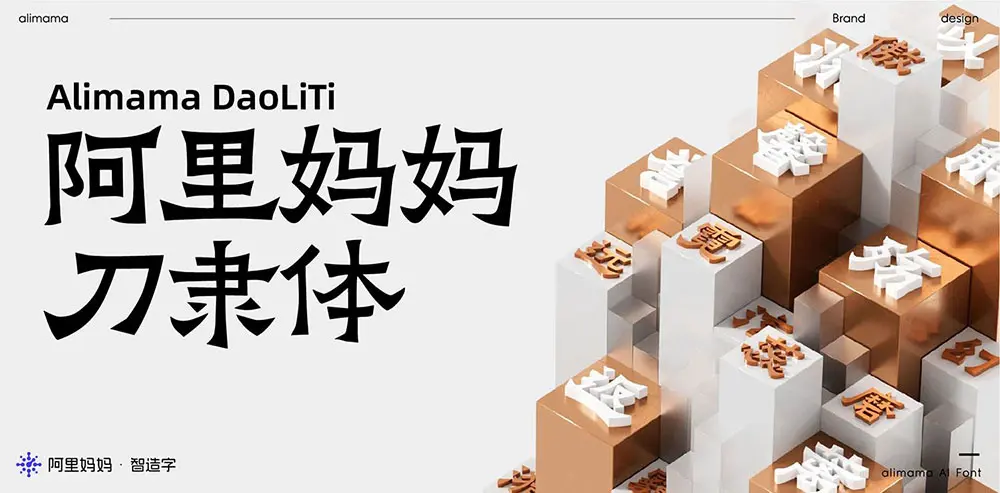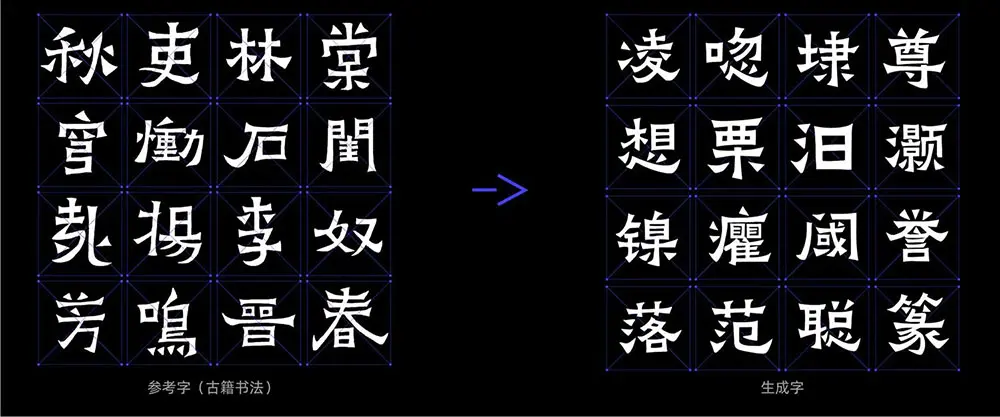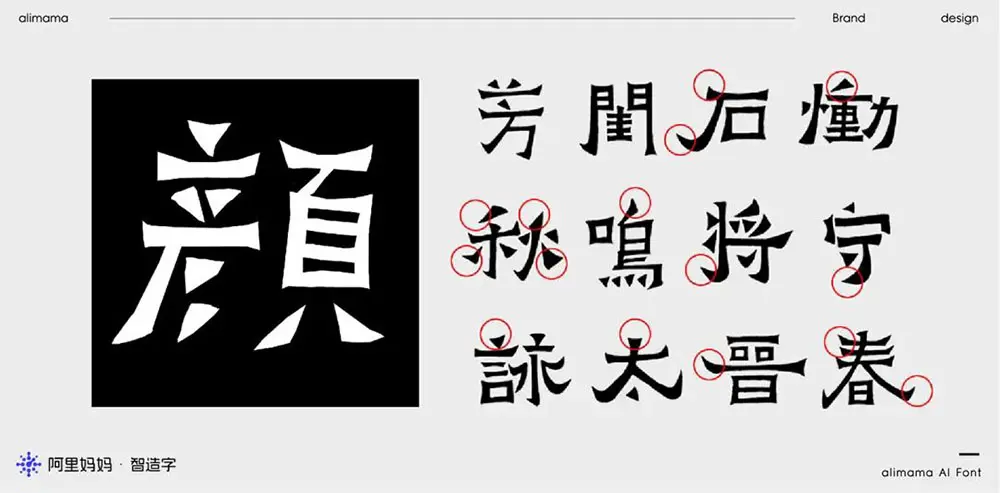
阿里媽媽刀隸體為中文簡體字庫,收納的中文字符包括但不限於GB2312,共計6763個漢字;英文大小寫共52個;常用標點符號共227個,總計7042個字符
設計說明:阿里媽媽刀隸體,通過機器學習了爨寶子碑的精髓,強調了三角點折彎與橫畫兩端“雁尾”之方強,外露鋒芒,耀其精神,介於隸楷之間,保持著濃重的隸書方筆意味,給人以堅實、朴茂、稚拙、倔犟之感,打破常規常態的勻稱均衡,結字極為大膽,大小常常出人意料,看似失度,實則深得藝理,險中求正,靜中寓動,動中求靜。